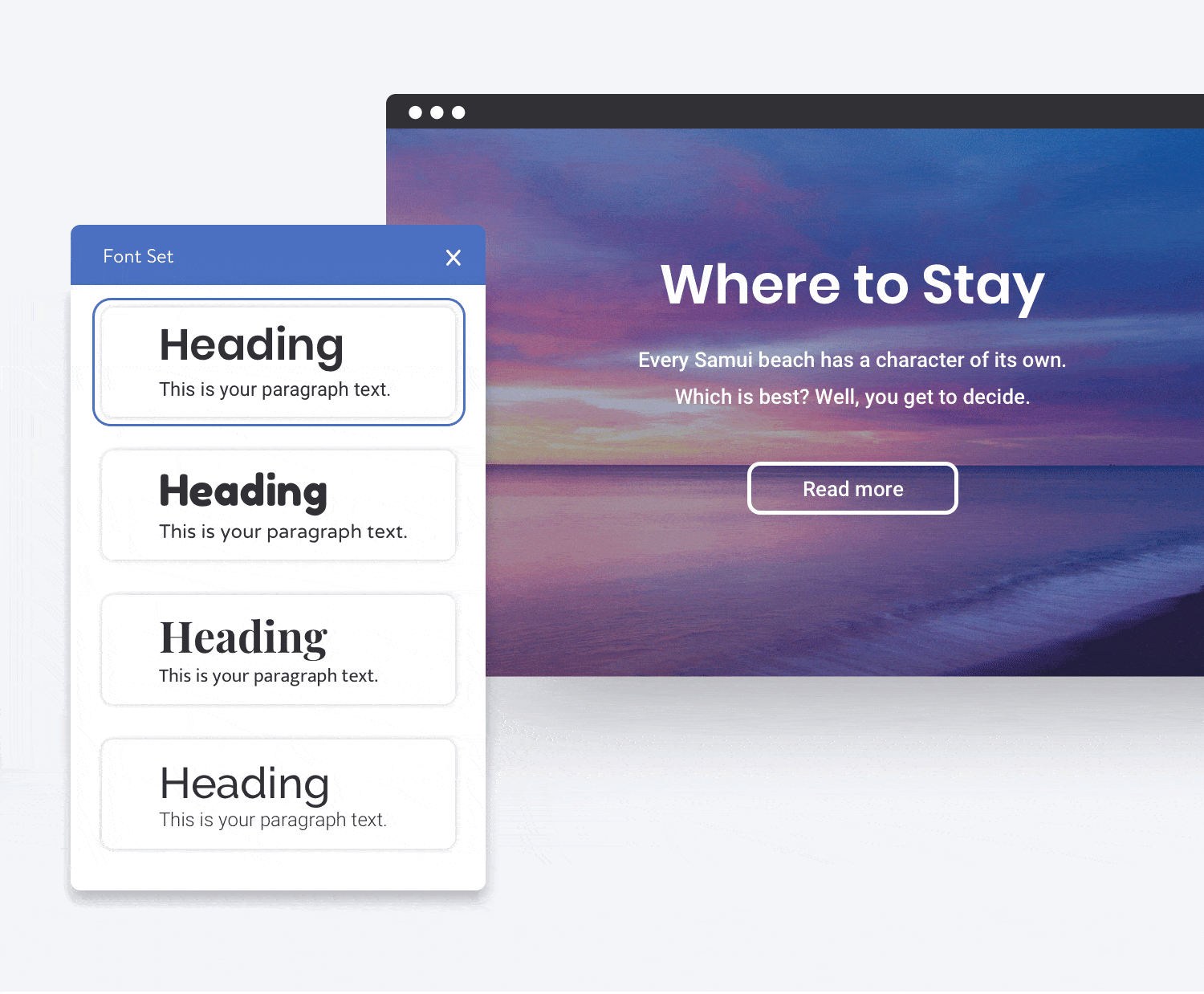
Mehr Schriftarten – mehr Stil: Die neuen Schrift-Kombinationen
Wer von seiner eigenen Idee überzeugt ist, möchte sie mit der Welt teilen. Und eine eigene Website ist dafür heute der entscheidende Schritt: Denn eure Website präsentiert online, wer ihr seid, was ihr macht und wofür ihr mit eurer Idee steht. Das Erscheinungsbild eurer Website wird damit auch ein Teil eurer (Marken-)Identität!
Ein prägender Aspekt dabei sind die Schriften: Welche Schriftarten repräsentieren euer Business am besten? Zu dieser Frage haben wir heute großartige Neuigkeiten: Unsere neue Schriften-Funktion macht es euch jetzt noch einfacher, eurer Website den idealen Look zu verpassen!
Mehr Schriftarten für euren persönlichen Stil
Wir lieben es, zu sehen, welche großartige Vielfalt an Jimdo-Seiten es gibt. Darum haben wir für euch auch eine große Bandbreite verschiedener Schriftarten zusammengestellt, die zum Design eurer Website passen – von Modern, über Elegant bis Fancy.
Die verschiedenen Design- und Schriftoptionen könnt ihr dabei ganz spielerisch ändern und ausprobieren. Ihr werdet sehen: Eure Website hat in jedem Fall einen schönen, konsistenten und stimmungsvollen Look!
Empfohlene Schrift-Kombinationen
Die richtige Schriftart für die eigene Website auszuwählen, ist, wie das perfekte Accessoire für sein Lieblingsoutfit zu finden. Je nach “Anlass” könnt ihr also auch bei der Wahl eurer Schriftarten denken, wie ein Stylist: Welche Schriften schmücken meine Website am besten?
Um euch möglichst viel Stylisten-Arbeit abzunehmen, empfehlen wir euch jetzt verschiedene Schrift-Kombinationen, die nach Meinung unserer Designer gut zu eurem Business passen könnten. Lasst euch inspirieren – und wählt einfach eure Lieblingskombination aus.
Standard Schriftgrößen
Bei Schriften, ja… spielt die Größe durchaus eine Rolle. Darum machen wir es jetzt ganz einfach, die Schriftgröße für den Text selber festzulegen. Ihr wählt einfach, ob klein, normal, medium oder groß am besten passt – fertig! Die Schriftgrößen passen sich automatisch der Bildschirmgröße des Besuchers an, sodass eure Überschriften sowie der Text immer ideal proportioniert sind.